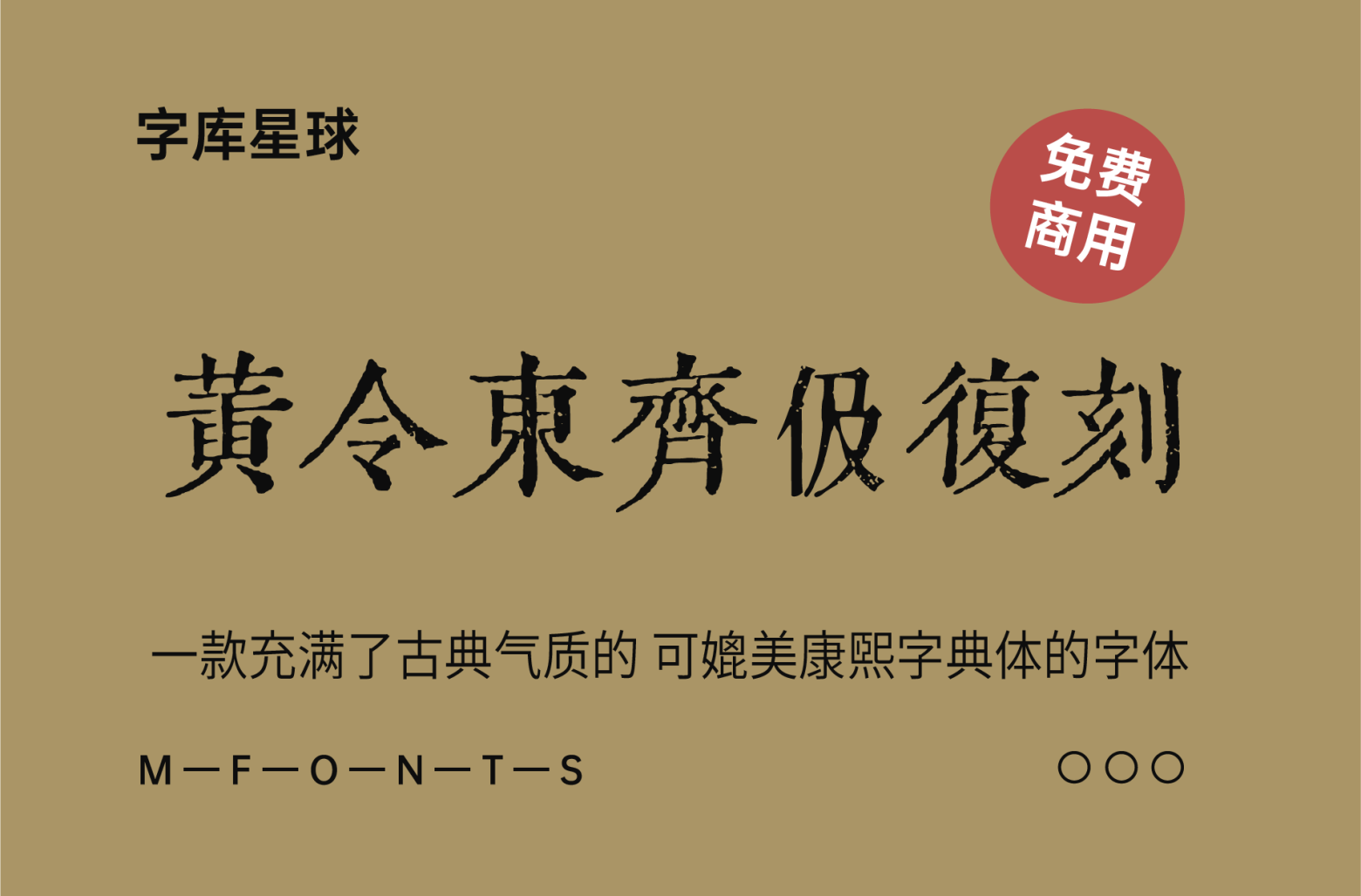
黄令东齐伋复刻
之前推荐过《黄令东齐伋体》给大家,这是一款充满了古典气质的,可媲美康熙字典体的字体,深受大家喜爱。而齐伋体是分两个版本的,一个是Combo版,一个是Fallback版。Fallback版本即之前介绍的黄令东齐伋体。为了方便区分,把Combo版本叫做黄令东齐伋复刻,这样比较容易理解。
黄令东齐伋复刻采用半自动计算机视觉和OCR对《李長吉歌詩》《淮南鴻烈解》进行扫描,通过程序处理后再手动选择适合的字型,最后导出成字体文件。
第一步:下载高分辨率 PDF(来自shuge.org)并将页面拆分为图像。
第二步:手动在每页上放置一个网格,以生成字符的边界框(可能可用自动角点检测算法代替)。
第三步:为网格上的每个字符生成一个低多边形蒙版,并保存缩略图(使用OpenCV)。首先,从灰度中减去红色通道,以清除用红色墨水打印的注释。接下来,对图像进行阈值处理并输入轮廓跟踪算法。然后使用度量来丢弃不太可能属于感兴趣字符的形状。(此步骤不会产生最终的字形,而只是进行快速而粗糙的提取以进行中间处理。)
第四步将每个缩略图逐一输入到神经网络中文 OCR 中进行识别(目前使用chineseocr/darknet-ocr,检测率低,准确率一般,CPU 速度很慢,正在寻找更好的替代方案)。
第五步:手动判断 OCR 的输出:选择给定字符的最佳实例,并标记错误识别的字符。
第六步:对于最终的字符集,自动生成每个字符的精细光栅渲染。通过从左到右以及从上到下累计像素,将每个字符置于其“视觉”中心,这样字符的“重量”就在中心线上,而不是将边界框置于中心。使用两种阈值方法,全局阈值被扩大并充当自适应阈值的掩码,从而保留细节
黄令东齐伋复刻是对古籍进行处理而得到的字体,所以只有繁体字形。在使用字体的过程中,如果输入简体字会直接映射成繁体字形。比如说你输入“汉”字,出来的结果会是“漢”字。这个结果不难理解,古人不会写简体字。